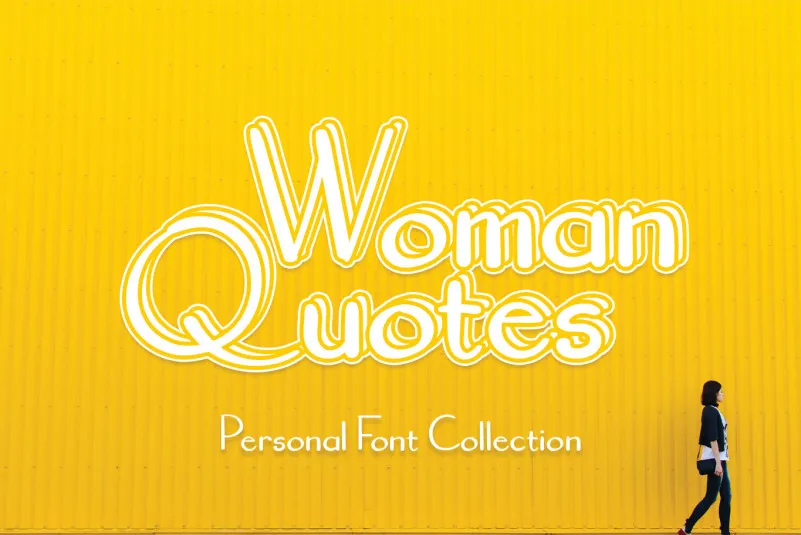
Woman Quotes Font – Download Grátis
Esta é uma fonte escrita a lápis, leve e descontraída, perfeita para aplicação nas tira-coroas de citações ou material didático. Ideal para crianças e projetos coloridos, esta fonte se destaca por sua simplicidade e informalidade. É ideal para quem deseja dar um toque único em suas criações digitais, seja para trabalhos escolares, desenhos infantis ou criação de materiais educativos, pois ela transmite uma atmosfera amigável e divertida que se adequa a qualquer contexto. Recomendada para designers gráficos buscando personalizar textos em um estilo retrô ou moderno, essa fonte é uma escolha perfeita para aqueles que buscam uma solução de texto que seja tanto funcional quanto criativa.